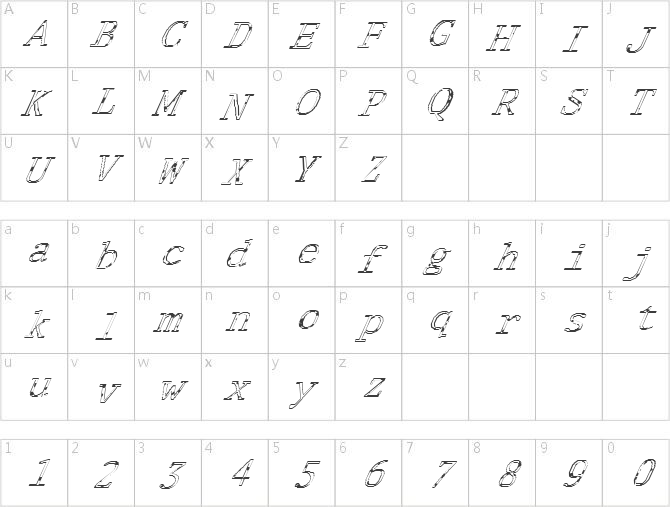
FZ DIGITAL 1 SPOTTED ITALIC 詳情頁
FZ DIGITAL 1 SPOTTED ITALIC字體字庫是一款讓人賞心悅目、百看不厭的英文字體,適合各類廣告和產(chǎn)品包裝設(shè)計應(yīng)用,字體大小0.13MB,格式為ttf字體,上傳用戶是洛洛,作者/版權(quán)方為未知